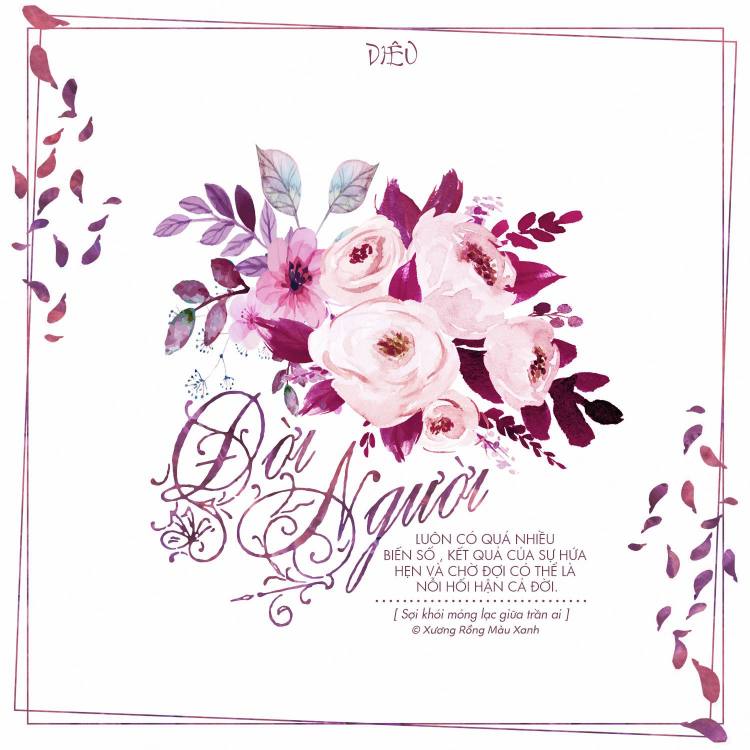
Giới thiệu về Font việt hóa MTD Antique Spenserian
Trong thế giới thiết kế đồ họa, việc lựa chọn một Font Chữ phù hợp đóng vai trò quan trọng trong việc truyền tải cảm xúc và thông điệp. Font việt hóa MTD Antique Spenserian là một trong những bộ phông chữ mang đậm phong cách cổ điển, được lấy cảm hứng từ lối viết tay Spencerian truyền thống của Mỹ. Bộ font này không chỉ mang lại vẻ đẹp quý phái, thanh lịch mà còn được tinh chỉnh để tương thích hoàn toàn với bảng mã tiếng Việt, giúp người dùng dễ dàng sử dụng trong các dự án sáng tạo mà không lo lỗi hiển thị.
Đặc điểm nổi bật của Font việt hóa MTD Antique Spenserian
Phong cách nghệ thuật tinh tế
MTD Antique Spenserian nổi bật với những đường nét thanh mảnh, uyển chuyển và các chi tiết bay bổng. Đây là lựa chọn lý tưởng cho các nhà thiết kế muốn tạo ra sự sang trọng cho các ấn phẩm như thiệp cưới, bìa sách nghệ thuật hoặc các chứng chỉ vinh danh tại trường học. Với cấu trúc chữ nghiêng đặc trưng, bộ font này gợi nhớ đến những bức thư tay xưa cũ nhưng vẫn giữ được sự hiện đại nhờ quá trình số hóa chuyên nghiệp.
Khả năng ứng dụng đa dạng
Dù mang hơi hướng cổ điển, Font việt hóa MTD Antique Spenserian lại có tính ứng dụng cực cao. Bạn có thể sử dụng nó để thiết kế logo thương hiệu cao cấp, làm tiêu đề cho các trang blog cá nhân hoặc trang trí menu nhà hàng theo phong cách vintage. Đối với các bạn học sinh và giáo viên, bộ font này sẽ giúp các bài thuyết trình trở nên sinh động và mang tính thẩm mỹ cao hơn, tạo ấn tượng mạnh mẽ với người xem ngay từ cái nhìn đầu tiên.